字体是文字的外在形式特征,也就是文字的风格,是文字的外衣。字体的艺术性体现在其完美的外在形式与丰富的内涵之中。网络上有成千上万的纹身字体,但快速的浏览显示,其中许多纹身字体的设计非常糟糕,毕竟是纹在身上的印记要谨慎多看图找字,找到合适的字体三思而后行。
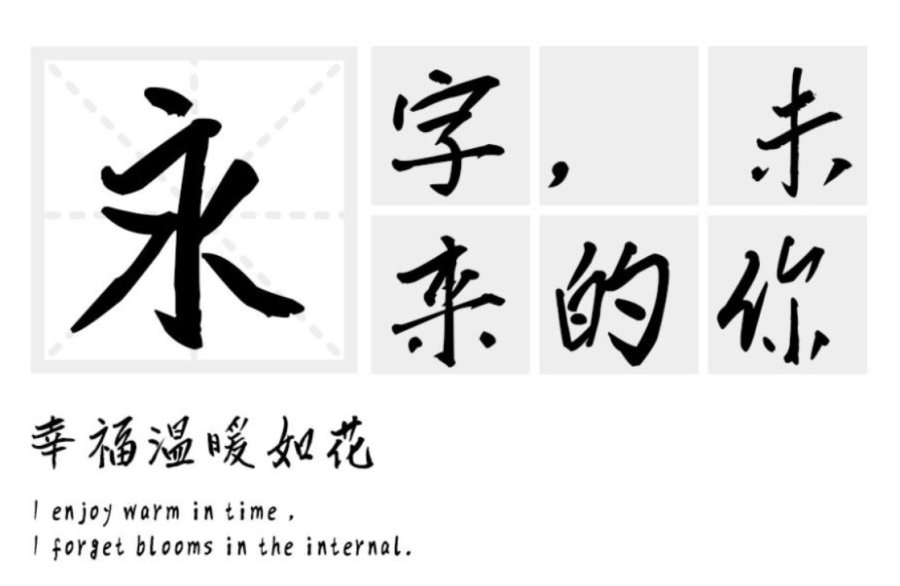
首先给大家介绍的是一款中文字体“汉标儒雅楷书”。字体个性鲜明,自然美观,典雅大方,结构严谨,比例合理,整体上给人一种舒展自如、赏心悦目的直观感受。使用在纹身设计上会加深纹身深刻的蕴意。
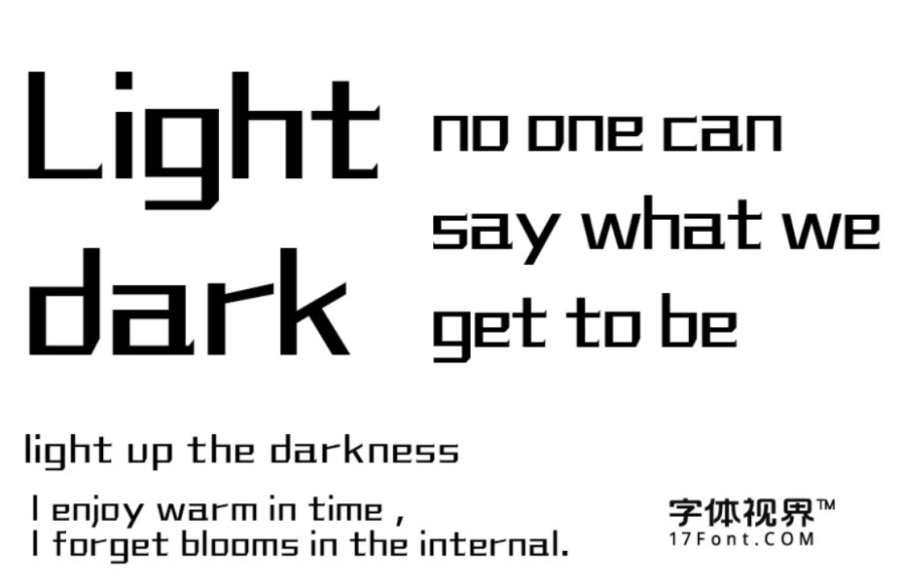
Witarna:Witarna字体笔画多为直线和对角线构成,圆弧处以直线剪切,彰显力量。字迹清晰笔画适当夸张。高识别度和观赏性,个性十足。
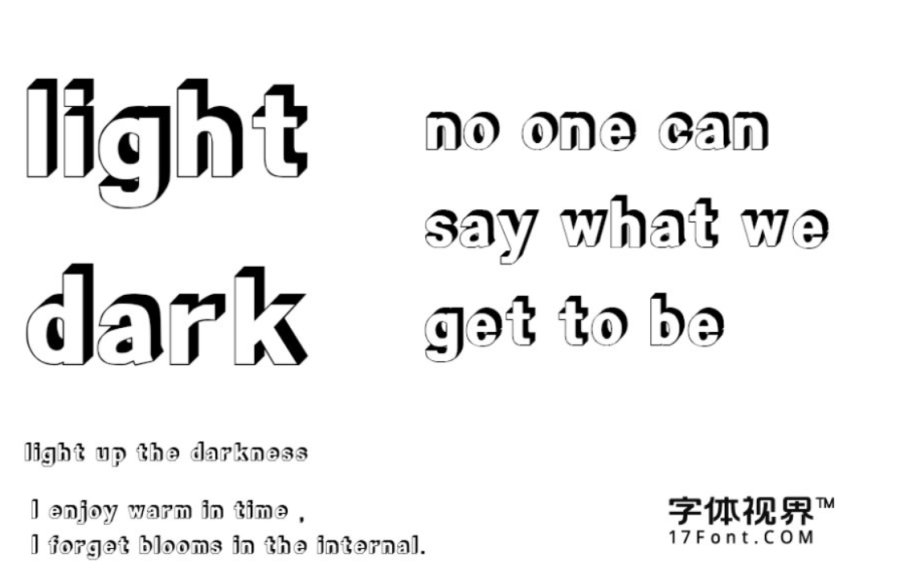
Elitakoo:这是一款空心字体,在直线对角线之间的平衡精心设计,字形厚重清晰易于字体识别。留白的设计感增加立体感,视觉效果丰富,作为纹身字体独具特色。